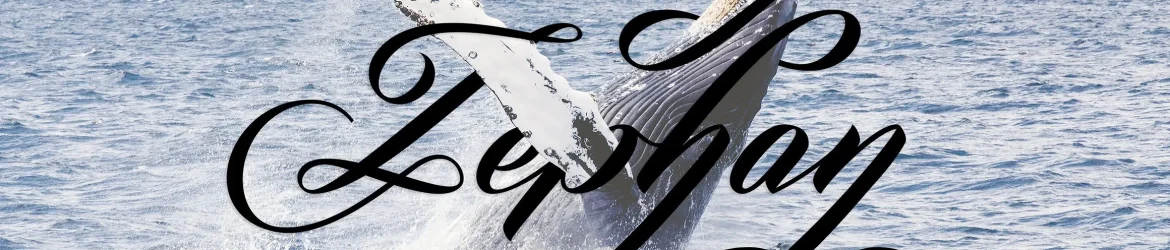
Zephan Script Font – Download Grátis
Introduzimos a nova fonte script Zephan Script Font criada pela Elementype. Esta novidade é perfeita para quem busca dar um toque único e elegante às suas criações digitais, seja para branding, logomarcas, cabeçalhos de página ou até mesmo em embalagens de produtos. Através da Zephan Script Font, você pode deixar seu texto ainda mais belo e envolvente, ideal tanto para projetos gráficos quanto para peças publicitárias. A sua capacidade única de dar um charme especial à sua tipografia torna-a uma fonte excelente para uso em rótulos de produtos ou até mesmo em cartões de visita. Zephan Script é a escolha perfeita para quem busca expressar personalidade e estilo em cada peça que criar. Seja para revolucionar seus logotipos, dar um novo significado às suas embalagens ou enriquecer os seus websites, esta fonte está aqui para fazer com que seu projeto brilhe ainda mais. Além disso, a Zephan Script Font foi desenvolvida de forma a ser ideal para uma variedade de usos. Seja para personalizar a aparência de sua newsletter, criar um design único para a sua publicação ou até mesmo em artigos digitais, essa fonte criativa se destaca por oferecer uma maneira única e encantadora de expressar seu trabalho. Neste contexto de design digital cada vez mais complexo, a Zephan Script Font é uma escolha ótima para designers e profissionais do design que buscam um toque único e sofisticado em suas criações. Não perca tempo; comece a explorar os infinitos possíveis com esta fonte atemporal e versátil.